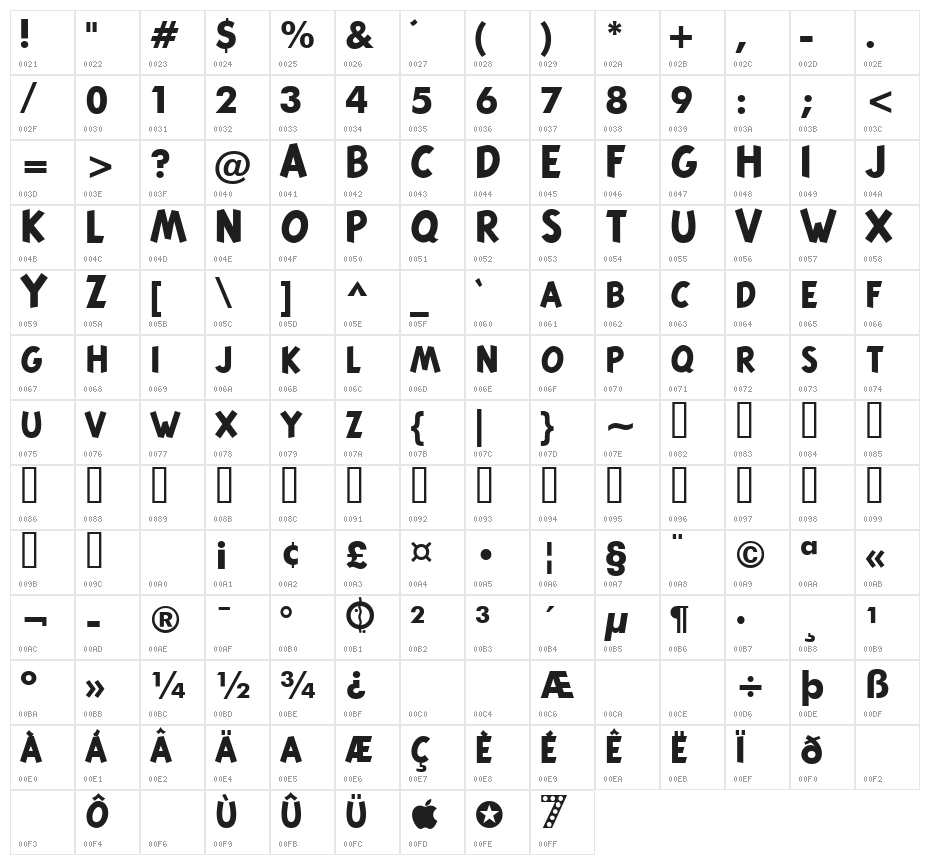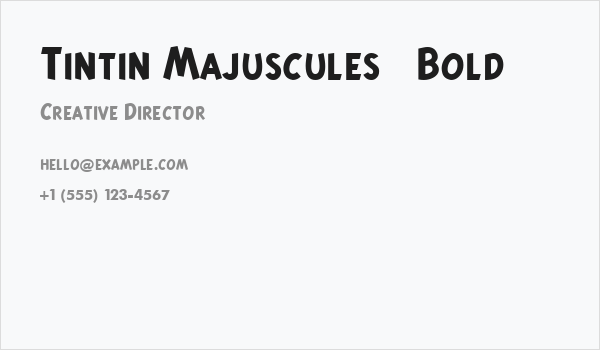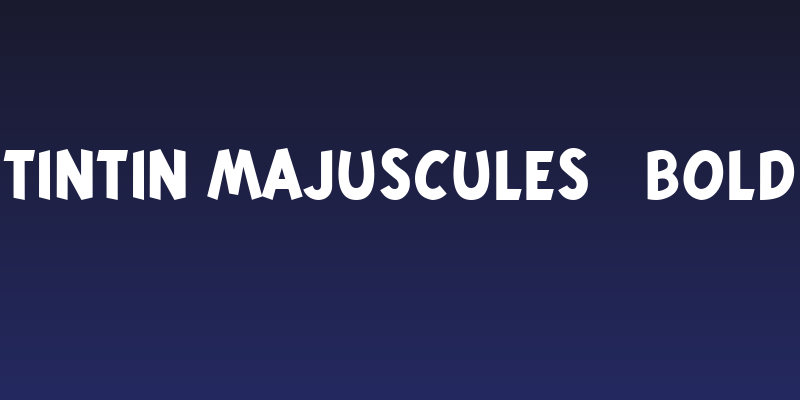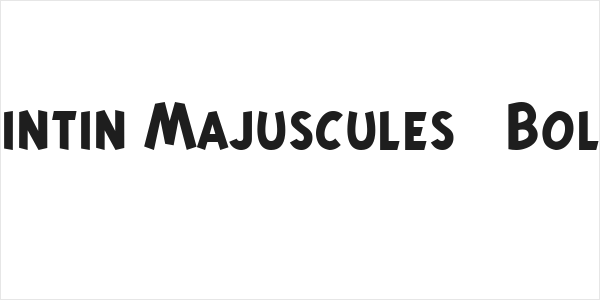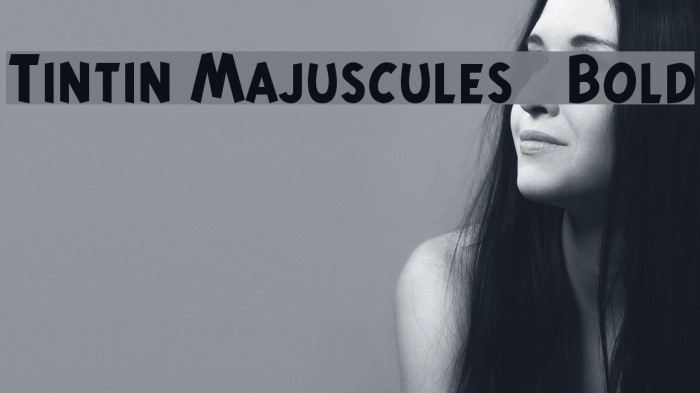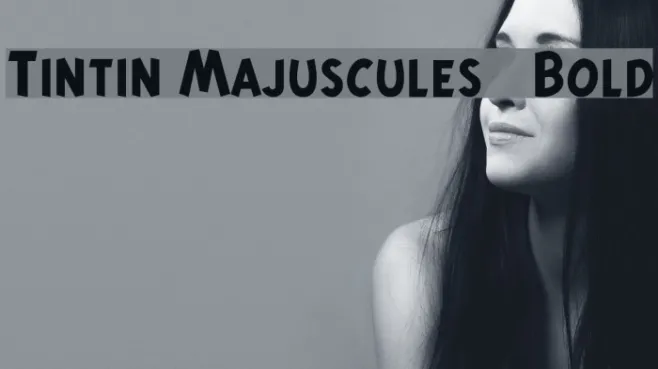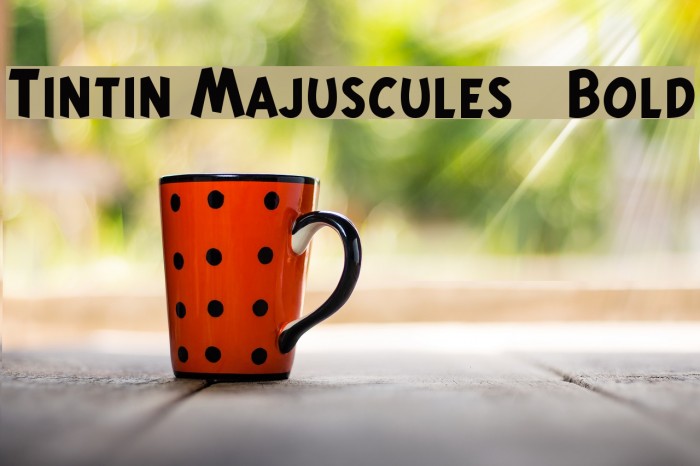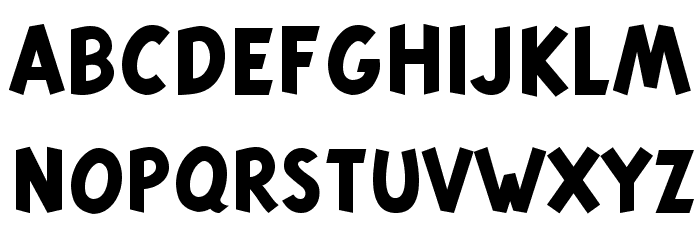
Tintin Majuscules Bold Font
| Stile generale | Playful, Bold, Dynamic |
| Progetti proposti | Ideal for headlines, logos, posters, and any design requiring a bold and playful aesthetic. |